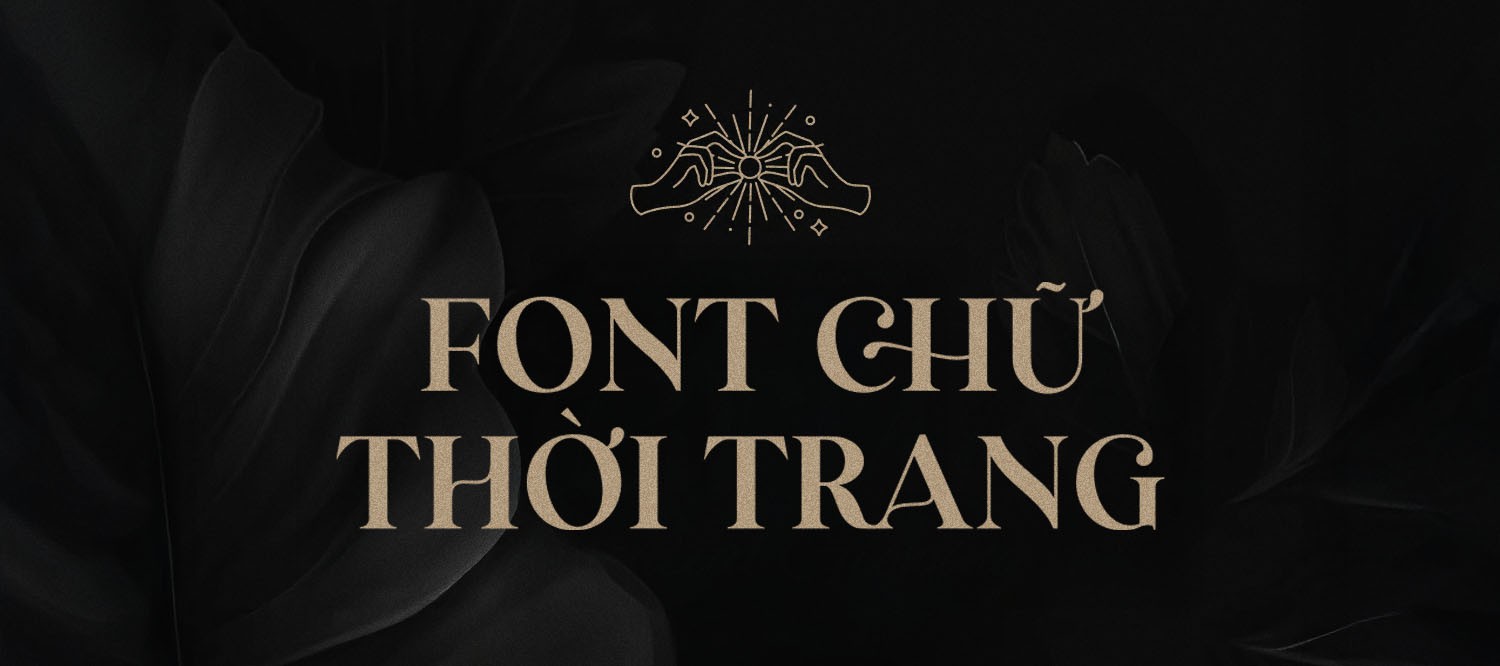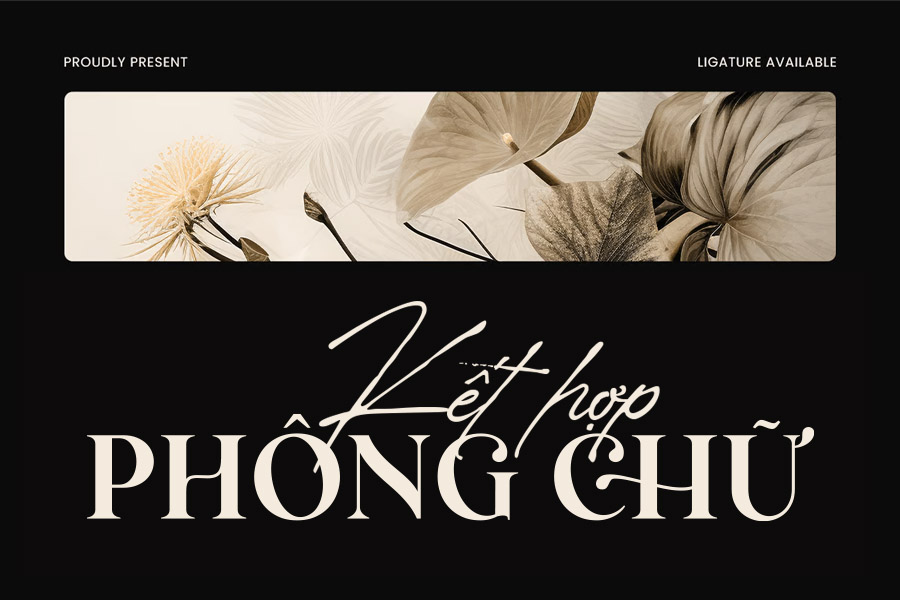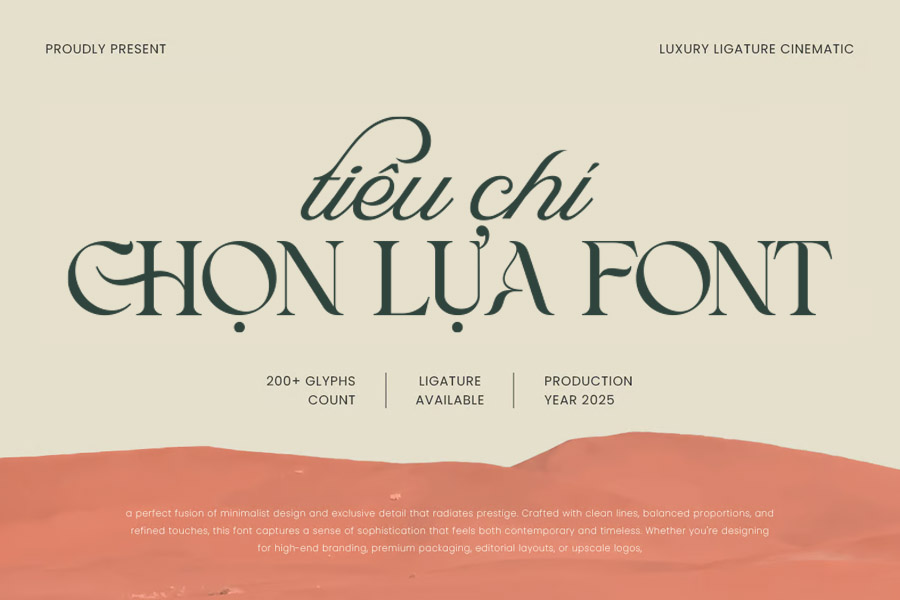
Font chữ thời trang không đơn thuần chỉ là những kiểu chữ đẹp; đó là những thiết kế mang tính thẩm mỹ cao, tinh tế và dễ nhận diện, giúp thể hiện cá tính, đẳng cấp và thông điệp của thương hiệu thời trang. Trong một thế giới mà thị giác đóng vai trò chủ đạo, việc lựa chọn đúng font chữ cho thương hiệu hay chiến dịch truyền thông thời trang là yếu tố sống còn để tạo ấn tượng và duy trì nhận diện lâu dài.
Các thương hiệu lớn như Dior, Chanel, hay Uniqlo đều đầu tư kỹ lưỡng vào bộ nhận diện font chữ của họ. Điều này cho thấy: font chữ không chỉ là yếu tố trang trí mà còn là "giọng nói" trực quan của thương hiệu.
Để một font chữ được xem là phù hợp cho ngành thời trang, đặc biệt tại thị trường Việt Nam, cần thỏa mãn các yếu tố sau:
Tính thẩm mỹ cao: Font phải mang phong cách sang trọng, hiện đại hoặc cổ điển một cách nghệ thuật, phù hợp với tinh thần thời trang mà thương hiệu theo đuổi.
Dễ ứng dụng: Font phải hiển thị tốt trên nhiều định dạng như in ấn, kỹ thuật số, biển hiệu, bao bì...
Hỗ trợ tiếng Việt đầy đủ: Các bộ font Việt hóa cần đảm bảo có dấu tiếng Việt chuẩn, không lỗi ký tự.
Font chữ hiện đại mạnh mẽ – TH The Mantra Key Việt hóa
Font TH The Mantra Key Việt hóa sở hữu thiết kế chữ in hoa cứng cáp, đường nét dứt khoát mang đậm tinh thần hiện đại và sáng tạo. Font thích hợp cho logo các thương hiệu thời trang unisex, mỹ phẩm hoặc startup sáng tạo.
Font chữ luxury cổ điển – TH Luxury 1 Việt hóa
TH Luxury 1 Việt hóa kết hợp giữa phong cách serif truyền thống và yếu tố hiện đại, tạo nên một thiết kế thanh lịch, cổ điển rất hợp với các thương hiệu cao cấp, spa, thời trang nữ.
Font chữ sang trọng thanh mảnh – TH Luxury 3 Việt hóa
TH Luxury 3 Việt hóa sở hữu các nét chữ thanh thoát, tinh tế và quý phái. Đây là lựa chọn hoàn hảo cho các thương hiệu thời trang nữ, túi xách hoặc mỹ phẩm có phong cách nhẹ nhàng, cao cấp.
Font chữ mạnh mẽ hiện đại – TH Cungcap 11 Việt hóa
Font TH Cungcap 11 Việt hóa có thiết kế vuông vức, rõ ràng, thích hợp làm logo cho các thương hiệu thời trang nam, phụ kiện kỹ thuật số hoặc nhóm ngành năng động, thể thao.
Font chữ sang trọng đậm chất cổ điển – TH Ginger Việt hóa
TH Ginger Việt hóa là một serif font có nét cổ điển, nữ tính, rất lý tưởng cho các logo thương hiệu thời trang thanh lịch, nước hoa hoặc sản phẩm handmade cao cấp.
Font chữ spa sang trọng – TH Luxury 7 Việt hóa
TH Luxury 7 là bộ font mềm mại, bay bổng nhưng vẫn đảm bảo sự sang trọng, phù hợp cho các tiêu đề trong lookbook spa, thẩm mỹ viện hoặc bộ ảnh thời trang nhẹ nhàng.
Font chữ tiêu đề thời thượng – TH Luxury 6 Việt hóa
TH Luxury 6 Việt hóa mang hơi hướng editorial cao, độ đậm vừa phải, đường nét tối giản nhưng tinh tế, rất phù hợp cho các thiết kế lookbook mùa lễ hội hoặc bộ sưu tập cao cấp.
Font serif cổ điển – SVN Bonvoyage Việt hóa
SVN Bonvoyage là một font serif cổ điển với các đường cong mềm mại, được Việt hóa chỉnh chu, thích hợp dùng trong tiêu đề tạp chí, các thiết kế retro sang trọng.
Font chữ hiện đại cho tiêu đề – TH Glowen Việt hóa
TH Glowen sở hữu kiểu dáng hiện đại, rõ nét, gợi lên sự chuyên nghiệp và chỉn chu – hoàn hảo cho tiêu đề trong các thiết kế thời trang nam hoặc các thương hiệu định vị quốc tế.
Font chữ spa hiện đại – TH Waking Việt hóa
TH Waking Việt hóa là bộ font mềm, nữ tính, dễ đọc và đặc biệt tỏa sáng khi dùng trong lookbook spa, mỹ phẩm hoặc các sản phẩm làm đẹp cao cấp.
Bộ font chữ sans-serif hiện đại – TH Guton Việt hóa (4 kiểu chữ)
TH Guton Việt hóa là bộ font gồm 4 style (Regular, Medium, Bold, Black), mang phong cách sans-serif hiện đại, sạch sẽ, dễ đọc và cực kỳ phù hợp với phần mô tả sản phẩm trên website, brochure hoặc bao bì.
Font chữ đơn giản dễ đọc – TH Vanban 1 Việt hóa
TH Vanban 1 Việt hóa được tối ưu hóa cho văn bản dài, giúp người đọc tiếp nhận thông tin một cách mượt mà. Đây là lựa chọn lý tưởng cho phần nội dung sản phẩm, thông số kỹ thuật, mô tả chi tiết.
Bộ font sans-serif hiện đại – Cobe Việt hóa (18 kiểu chữ)
Cobe Việt hóa mang đến 18 phong cách chữ đa dạng, từ Light đến ExtraBold, giúp linh hoạt ứng dụng cho nội dung mô tả sản phẩm, tiêu đề phụ và thiết kế UI website.
Font chữ thân thiện – Verdana Việt hóa
Verdana Việt hóa là font chữ kinh điển, quen thuộc với giao diện web, dễ đọc, tương thích cao, lý tưởng cho nội dung mô tả sản phẩm, HDSD, hoặc các mục phụ trợ.
Có bao nhiêu nhóm chính? Tối thiểu 4 nhóm: logo, tiêu đề, mô tả, quảng cáo.
Font serif hay sans-serif phù hợp hơn với lookbook? Serif cho luxury, sans-serif cho hiện đại trẻ trung.
Có nên dùng font thời trang cho poster phim? Có – nếu chủ đề phim mang yếu tố thị giác mạnh hoặc nghệ thuật.
Lựa chọn đúng font không chỉ tạo dấu ấn thị giác mà còn là tuyên ngôn phong cách của thương hiệu bạn. Đừng ngại thử nghiệm và kết hợp – hãy biến font chữ thành "bộ mặt" độc bản cho thương hiệu thời trang của bạn!